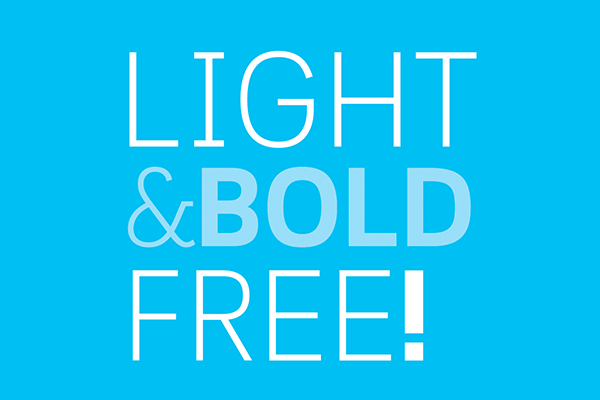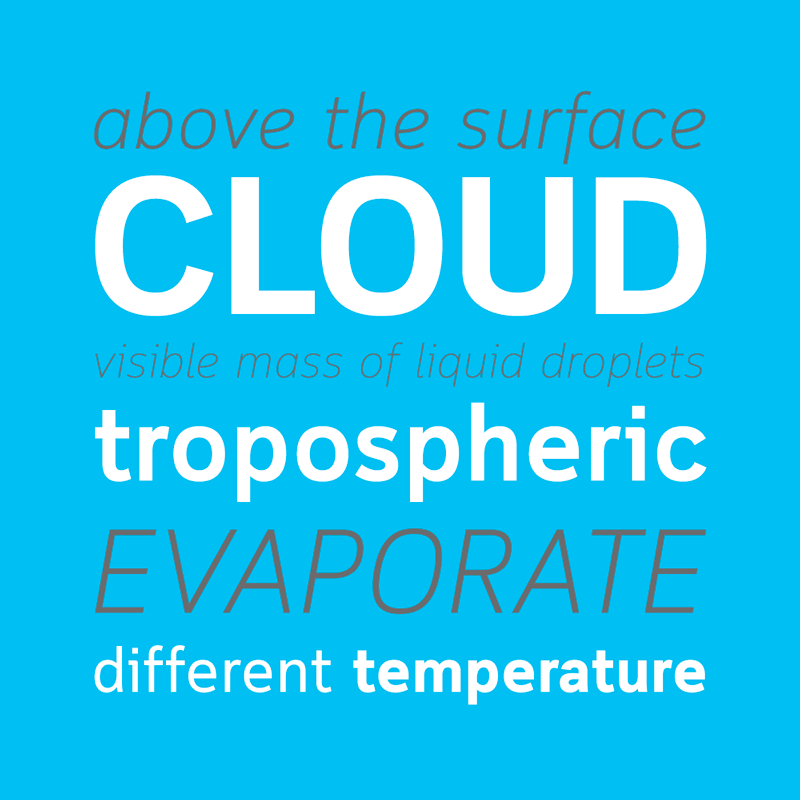
Cloud Sans字体
Cloud Sans是一款由泰国设计师Typomancer创作的无衬线英文字体。这款字体具有人文主义风格,带有一些独特的结构,适用于各种通用场合。全字体家族包括5个字重和斜体,其中Light和Bold两个字型已经打包在下载文件中,并且可以免费商用。这款字体将为您的设计带来优雅而独特的视觉效果,非常适合用于现代、简洁、时尚的标识、海报、品牌形象等设计项目中。现在就免费下载Cloud Sans字体,让您的创意焕发独特的魅力吧!
Cloud Sans效果预览
Cloud Sans字体效果预览